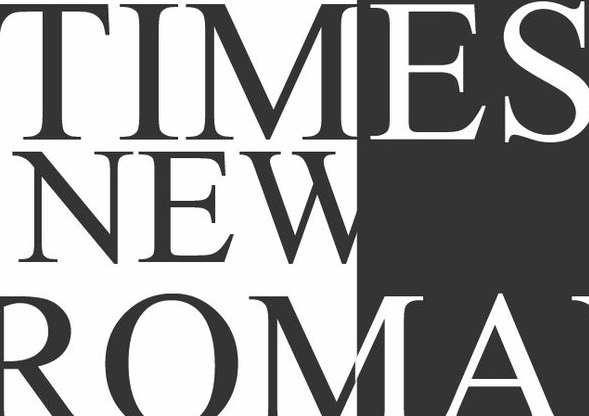
Российским клиентам заблокировали шрифты Times New Roman и Arial
Компания Monotype закрыла россиянам доступ к Times New Roman и ещё четырём популярным шрифтам
Компания Monotype перекрыла для россиян доступ к библиотеке на своём сайте. В результате пользователи из РФ оказались лишены доступа к популярным шрифтам Times New Roman, Arial, Verdana, Tahoma и Helvetica, правами на которые владеет американская фирма. Об этом сообщают «Ведомости» со ссылкой на источники в IT-компаниях.
По имеющимся данным, при попытке входа на страницу с каталогом шрифтов пользователь получает сообщение о запрете доступа. При включении VPN эта проблема исчезает, и каталог становится доступен.
Один из наиболее известных в мире шрифтов Times New Roman был разработан в 1932-м типографом Стэнли Моррисоном и художником Виктором Лэрдентом. Его стали использовать в газете The Times, это способствовало большему удобству чтения и позволило сэкономить пространство.
До 2007 года шрифт использовался по умолчанию в операционной системе Microsoft.
Также он используется в качестве официального шрифта для документов Госдепартамента США и Минобороны РФ.